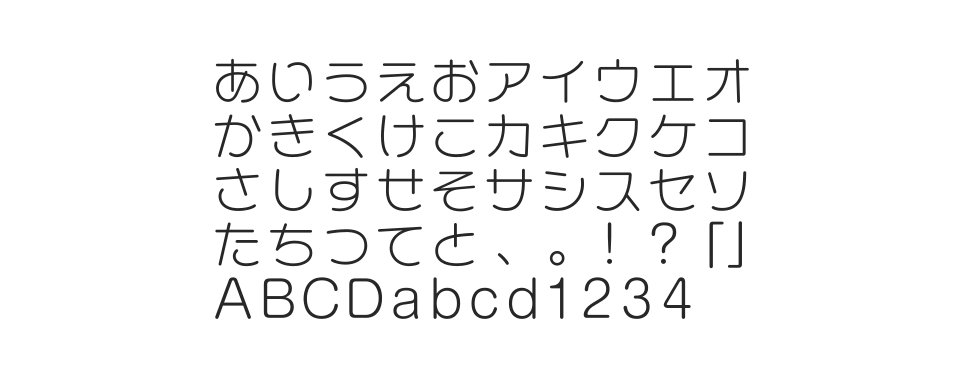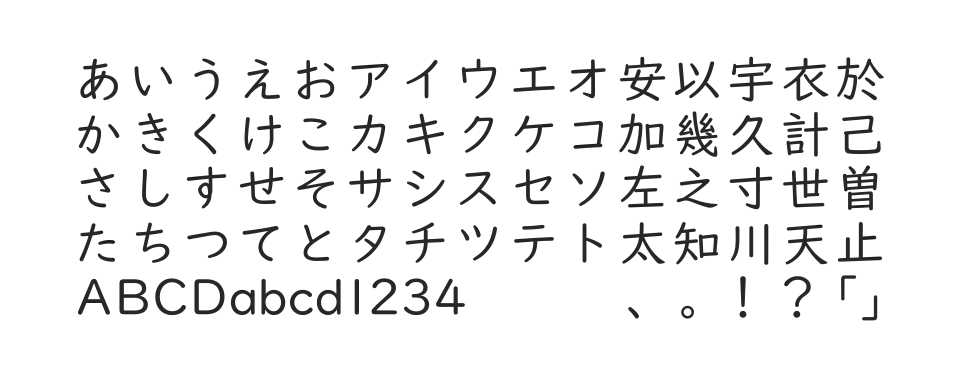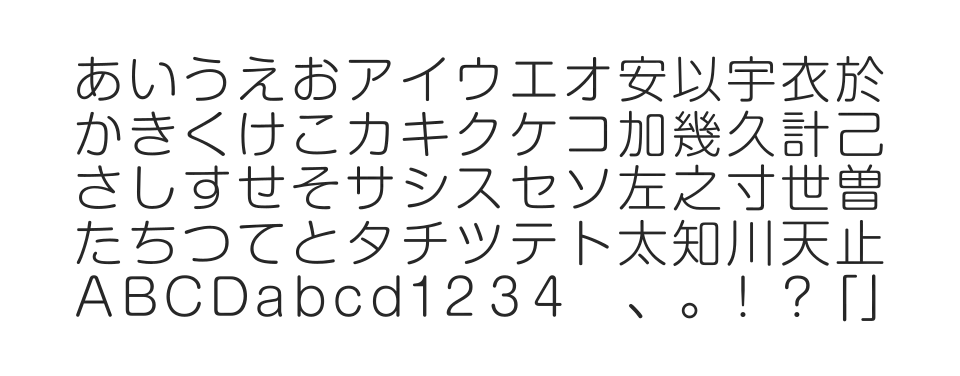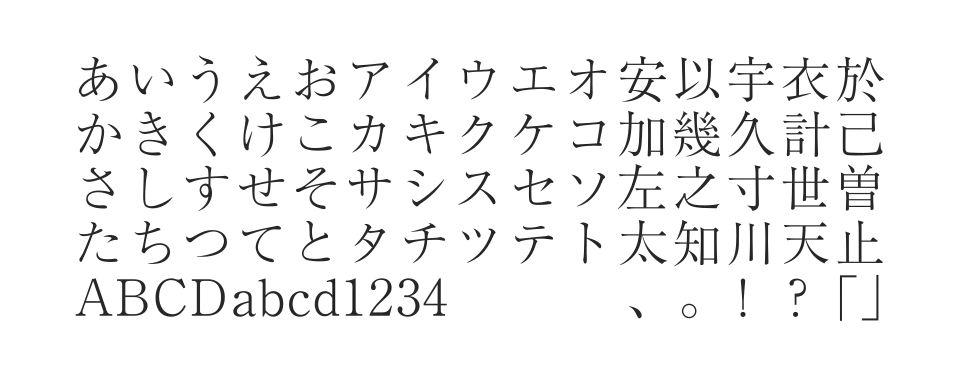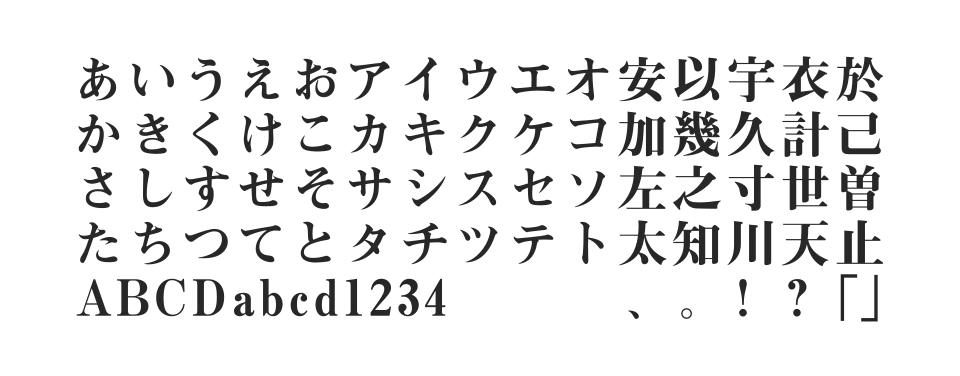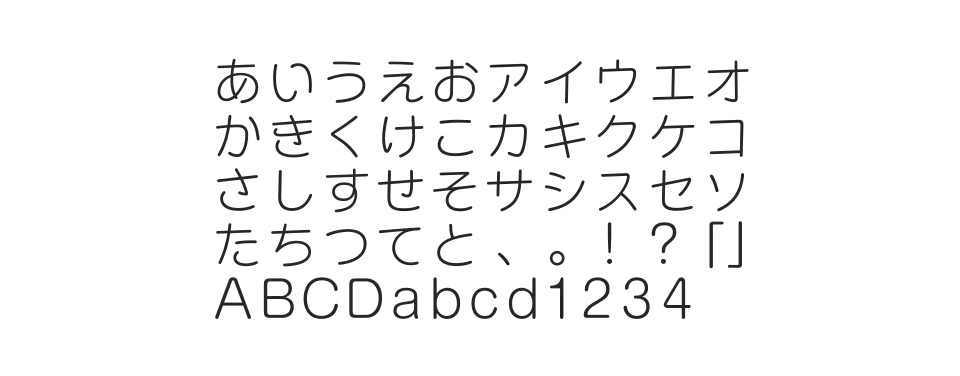
写真植字用に開発されたゴシック体。基本7書体の一つとしてグラフィックデザインでスタンダードに使用。シャープな印象で広告コピー用に採用多数。
手書き文字のようなあどけなさが持ち味のかな書体。やわらかく親しみやすいストロークで、店頭POPやパッケージ、子供向け製品に最適。
重厚さと風格を備えた伝統的な見出明朝体。確かな太みと存在感をもつ漢字と細めのかなの対比により高い可読性を実現。見出し用途に最適。
森川龍文堂明朝体をベースにしたスタンダードな明朝体。金属活字由来の彫刻刀の冴えと親しみやすい雰囲気を両立。DTPの基本書体として定評。
システマチックな雰囲気を持つ現代的なゴシック体。装飾のない均質で明るいデザインが特徴。公共サインからパーソナルユースまで広範囲に対応。
新ゴをベースにした丸ゴシック体。明るく洗練された雰囲気に丸みのある親しみやすさが特徴。広告から見出し、サインまで多彩なシーンで活躍。
学習指導要領準拠のユニバーサルデザイン書体。JIS90字形をデフォルトとし、教育現場での使いやすさを重視。読み書き困難への配慮も充実。
学習指導要領に準拠し、読みやすさを重視したユニバーサルデザイン書体。ディスレクシアやロービジョンに配慮したデザインで、デジタル教科書やICT教育に最適。
丸いエレメントが楽しいポップなかな書体。手書き文字風のデフォルメで、子供っぽさやかわいらしさを演出。広告見出しやPOPに最適です。
学習指導要領に準拠したユニバーサルデザイン書体。ロービジョンやディスレクシアに配慮し、ICT教育の現場に最適化された教育専用フォントです。